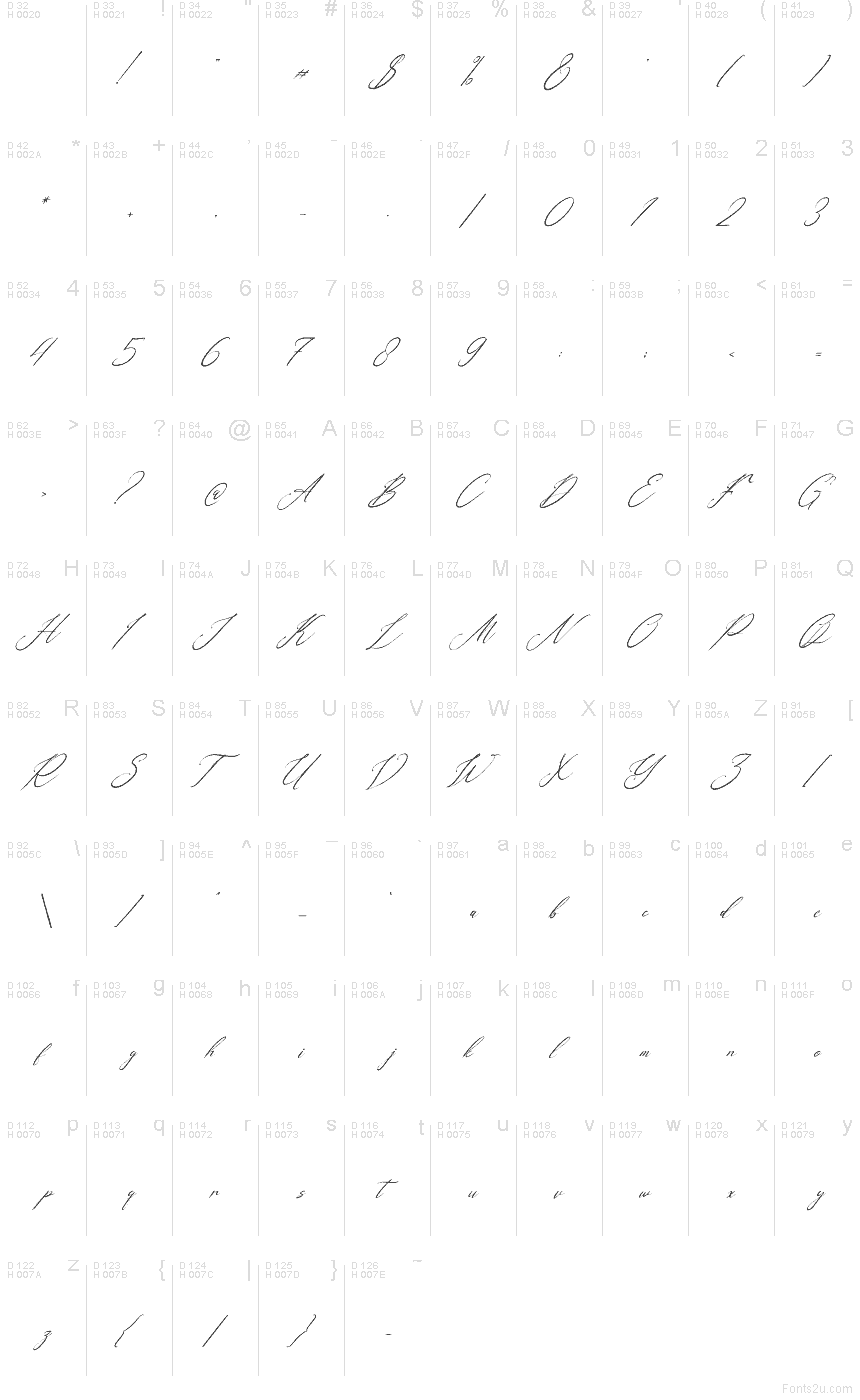
Geraldyn Brushko Italic
Geraldyn Brushko Italic de Denustudios est une police calligraphique gratuite caractérisée par de longs balayages aériens et un rythme manuscrit décontracté qui permet à chaque mot de se déployer harmonieusement sur la ligne. Son mouvement évoque davantage le lettrage au pinceau vif qu'une calligraphie formelle, avec des boucles élancées et des traits effilés qui confèrent à l'ensemble légèreté et fluidité.
Elle est idéale pour des logos signatures, des packagings de boutique, des en-têtes d'invitations, l'image de marque dans l'univers de la beauté ou des citations pour les réseaux sociaux, où son tracé étendu encadre les phrases avec élégance. Puisque les lettres s'étirent longuement avant de revenir sur elles-mêmes, cette police est la plus convaincante lorsqu'elle a de l'espace pour respirer et servir d'élément décoratif principal.